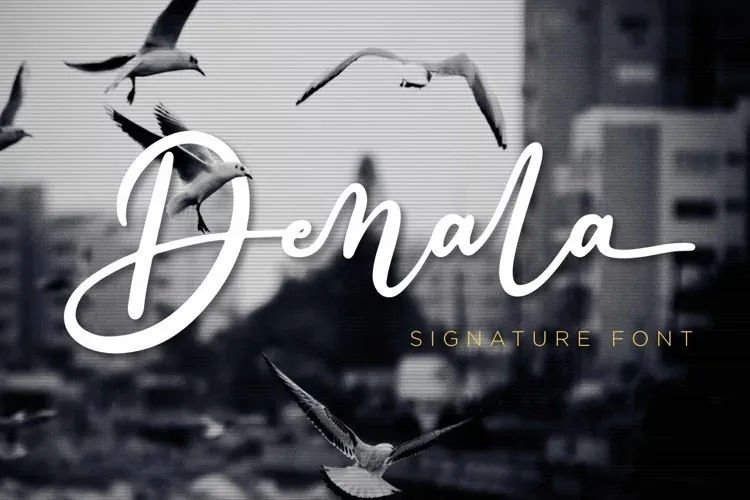
A Denala Font é uma elegante tipografia script criada pela Attype-Studio, com traços que acabam em espiral. Esta tipografia foi cuidadosamente meticulosa e detalhada. Perfeito para quem deseja explorar a versatilidade dessa fonte incrivelmente única, ela é perfeita para criar designs de tirar o fôlego. Uma ótima escolha para qualquer projeto que busque estilo e sofisticação. Não hesite em experimentá-la para adicionar aquele toque especial a seus trabalhos.